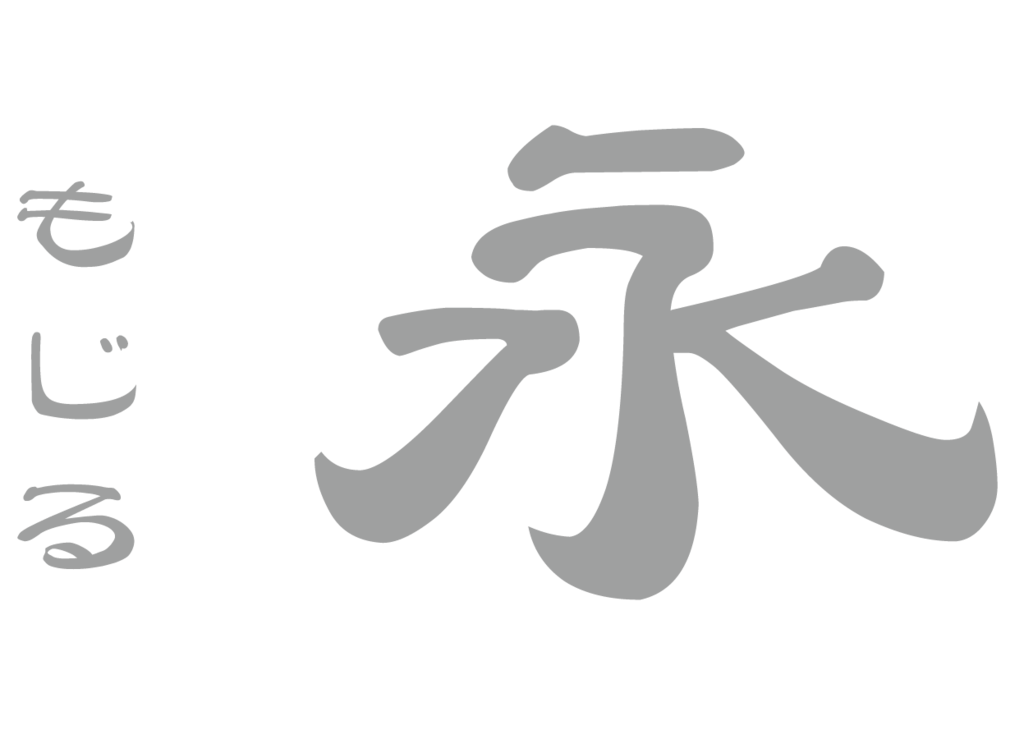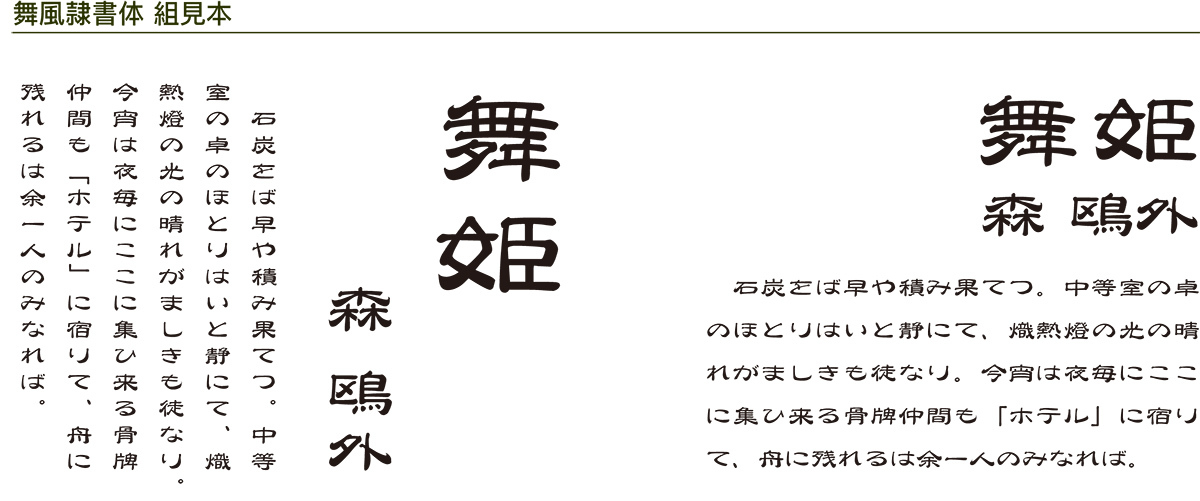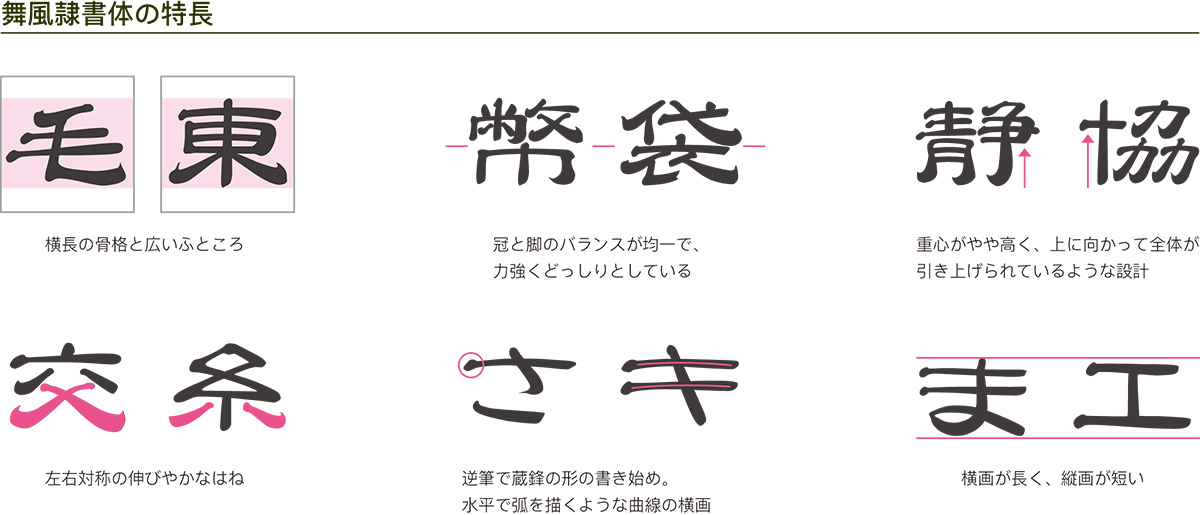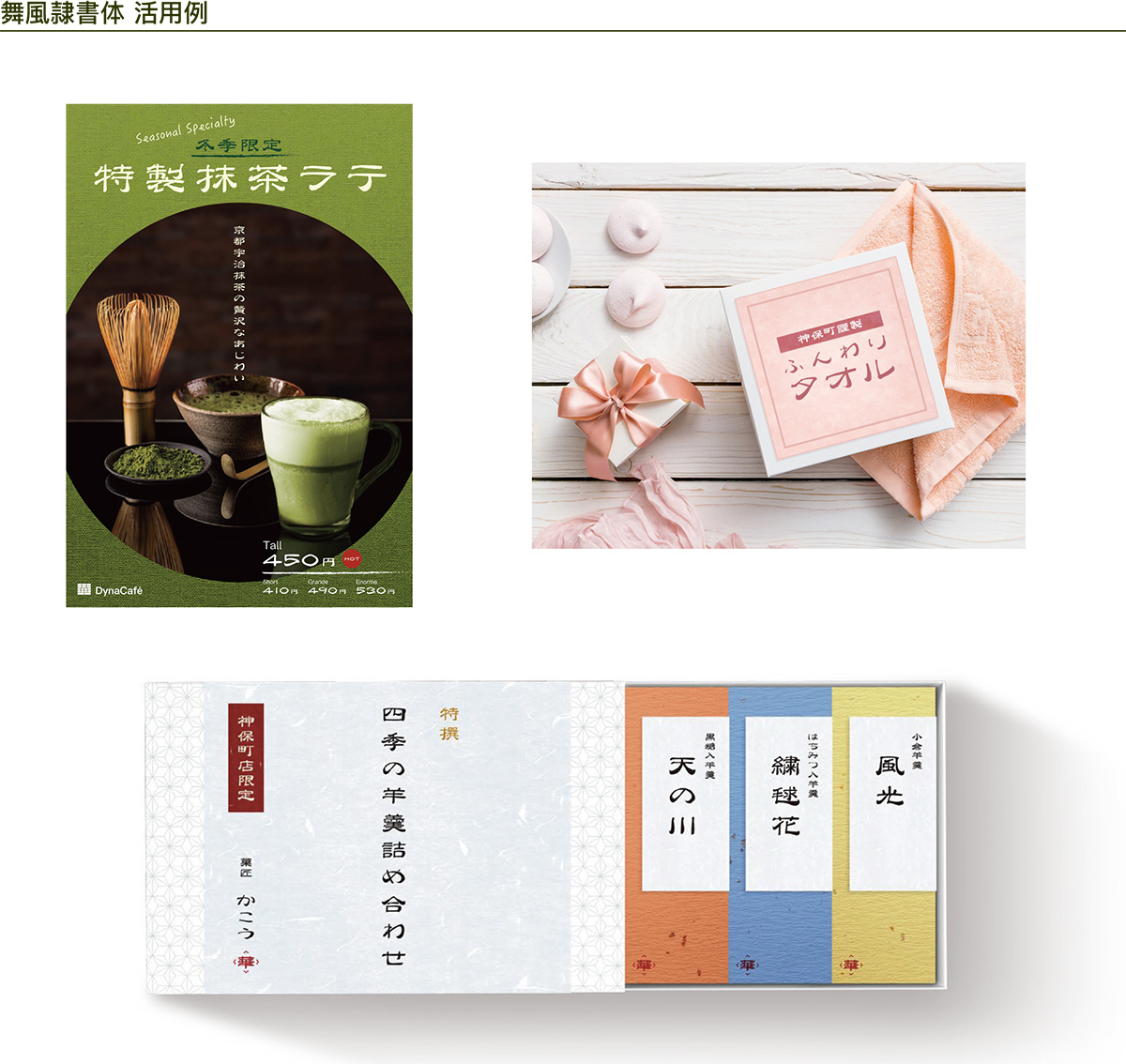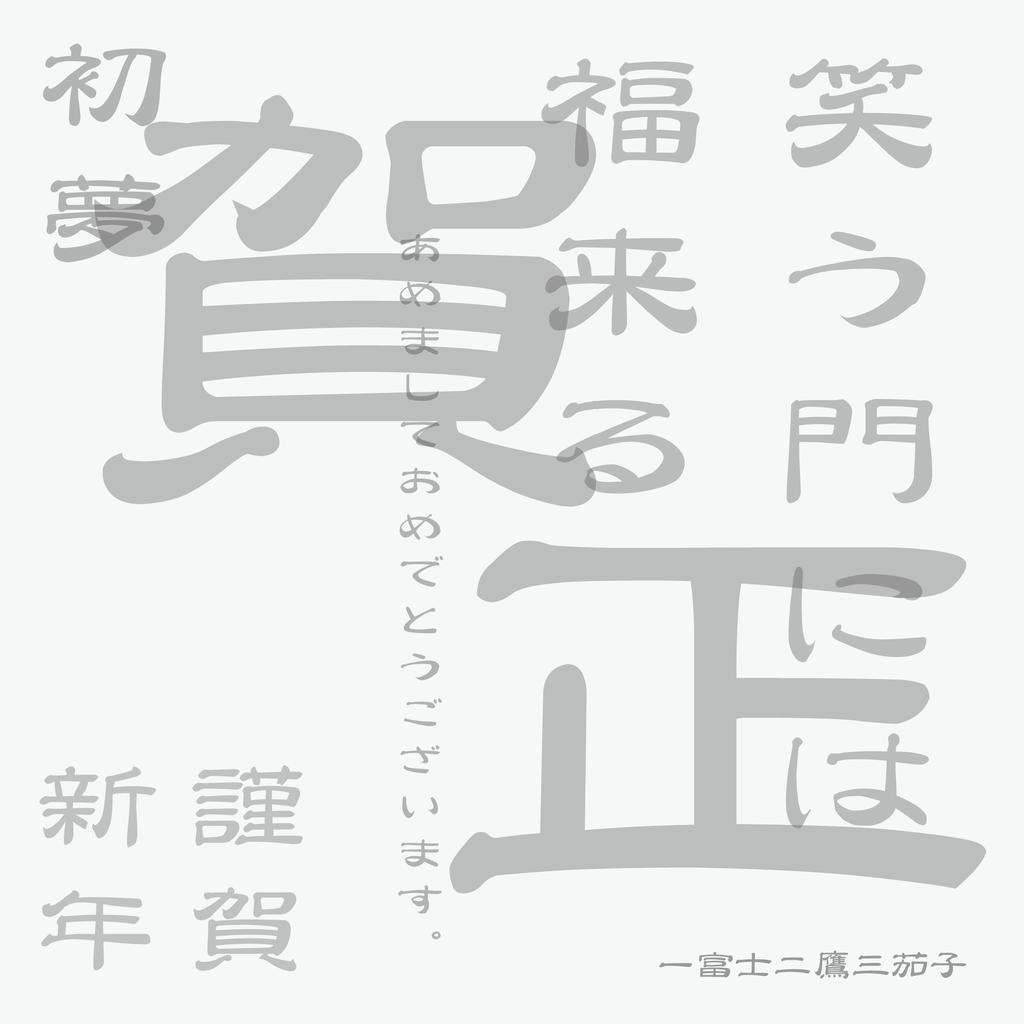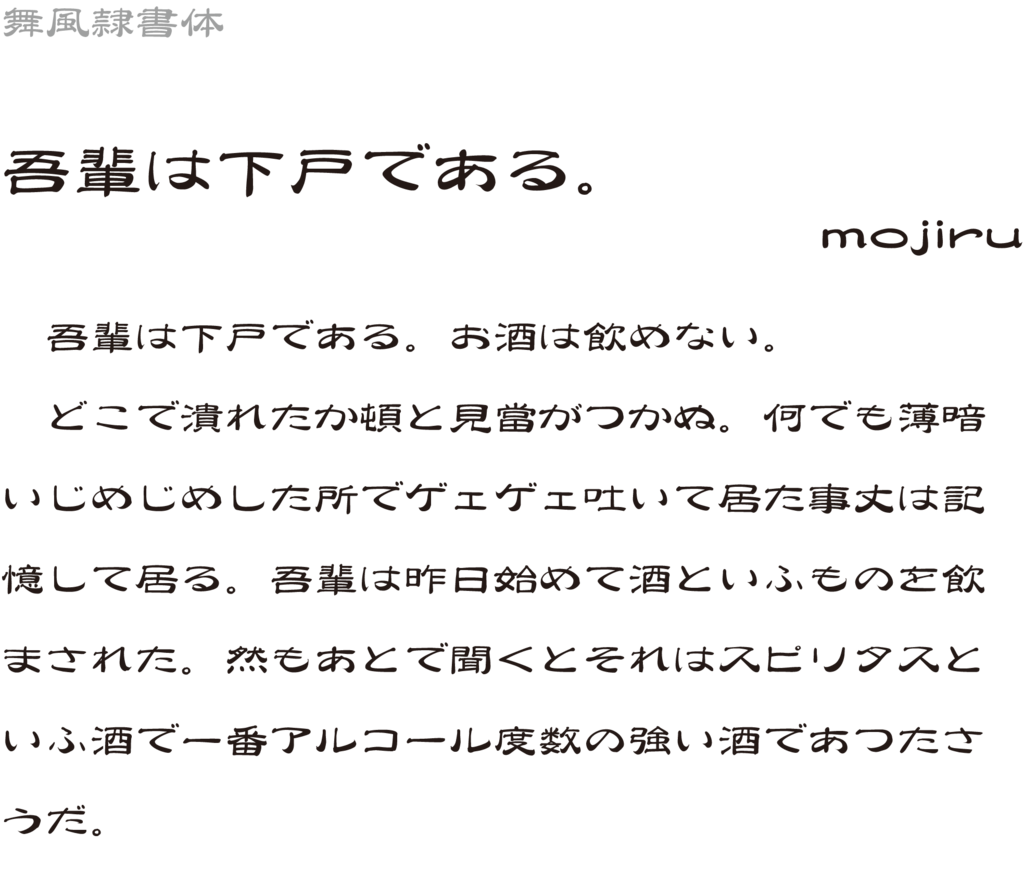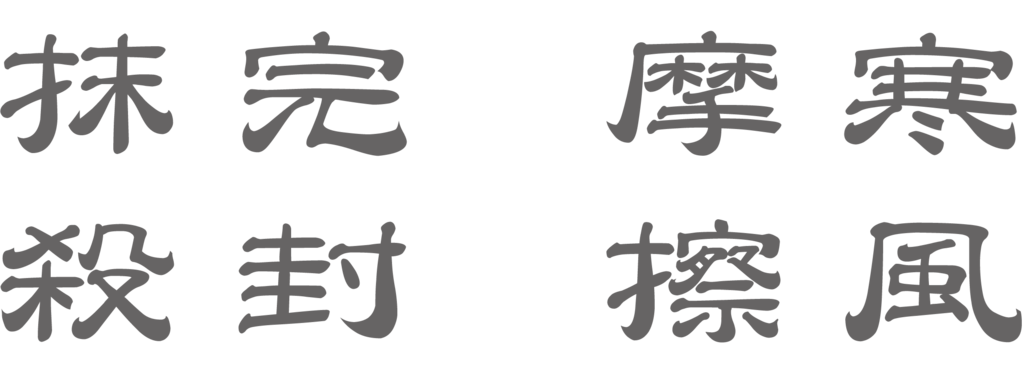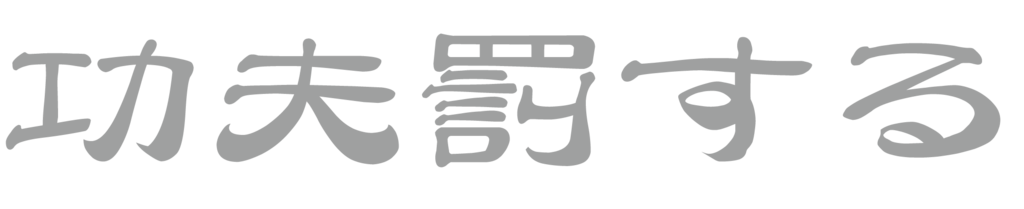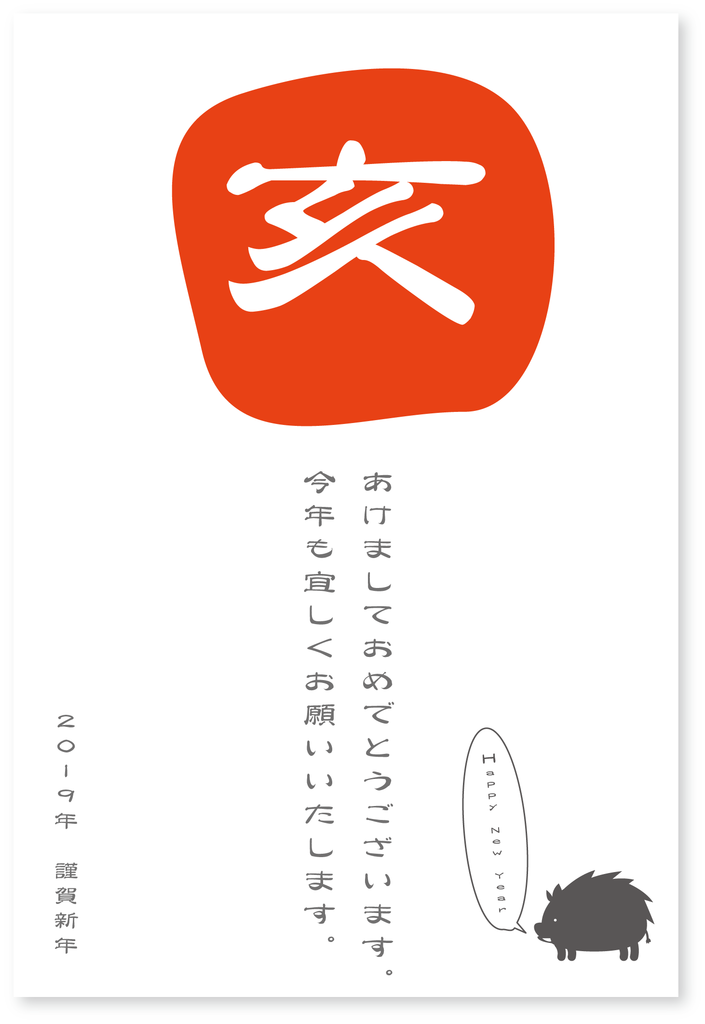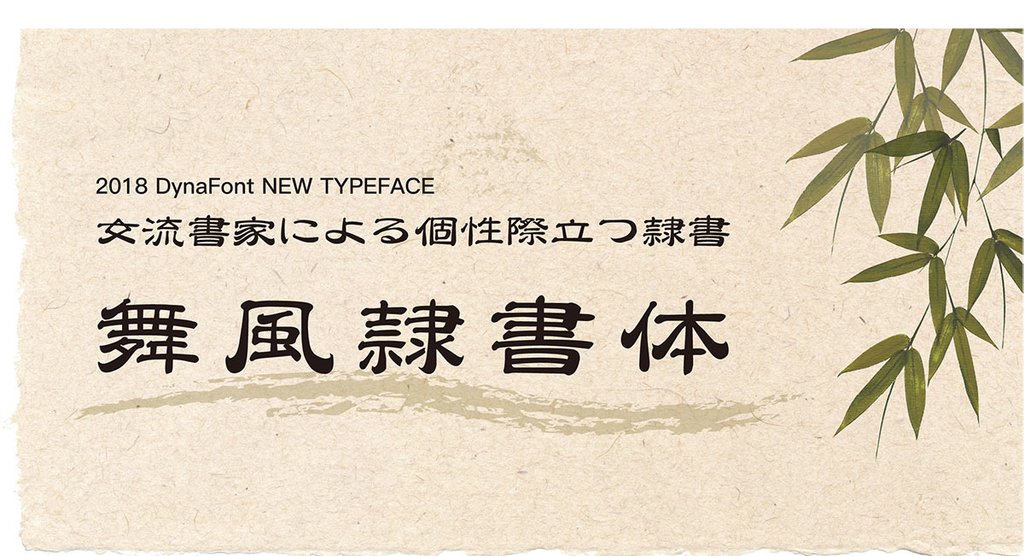
舞風隷書体
「舞風隷書体」は、女流書家による豪快なはらいが特徴の個性あふれる隷書体。
伝統的な書道の様式を基に隷書体特有の横長の骨格と波打つような運筆である波磔を取り入れ、力強さの中にも躍動感のある運筆で、伸びやかなはらいと滑らかな提按(上げ、押さえ)といった隷書体の個性を際立たせ、文字の美しさを表現している。
「舞風隷書体」は、伝統的な書道の様式を基に隷書体特有の横長の骨格と波打つような運筆である波磔を取り入れ、力強さの中にも躍動感のある運筆で、伸びやかなはらいと滑らかな提按(上げ、押さえ)といった隷書体の個性を際立たせ、文字の美しさを表現した書体。
「舞風隷書体」書体見本
ザッと使用してみた感想は、なかなかクセの強い隷書体といった感じだった。
舞風隷書体で年賀状見本を作成
平成最後の2018年11月に突如登場したダイナフォントの隷書体「舞風隷書体」。筆書体ということで、年賀状にも相性が良さそうな気がしたので年賀状見本を作成してみた。
書体の太さがW7ということもあり、そこまで太さは感じない。